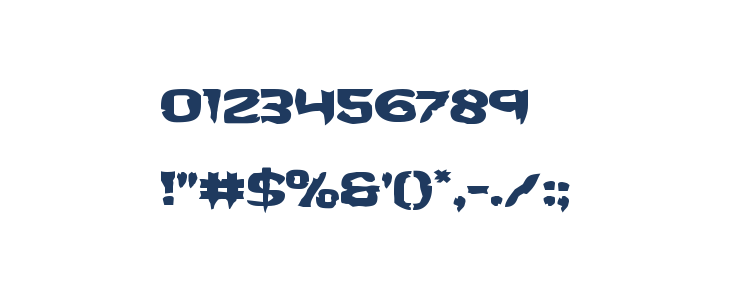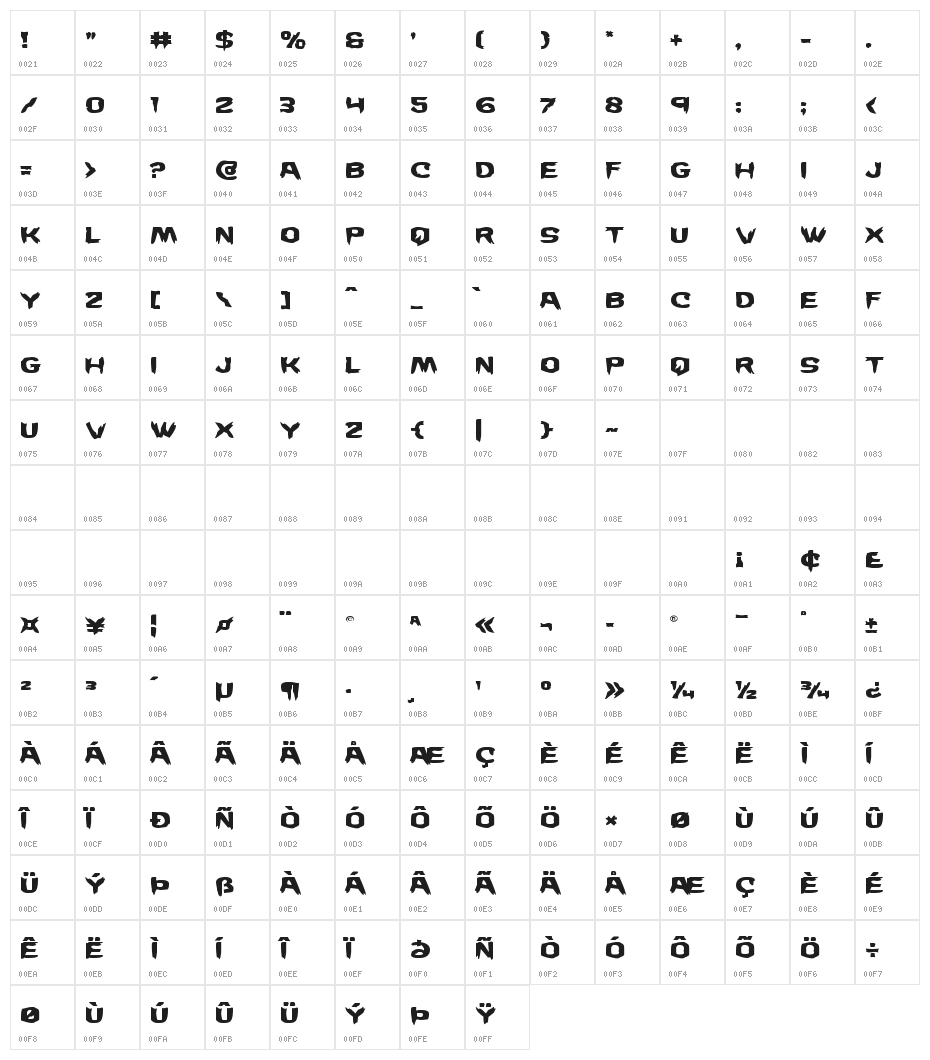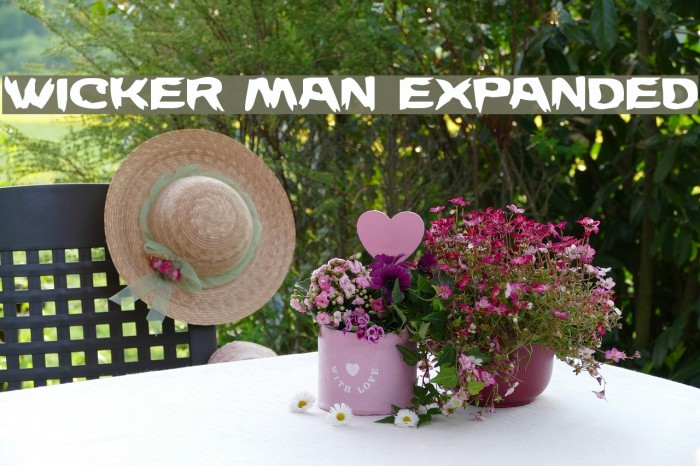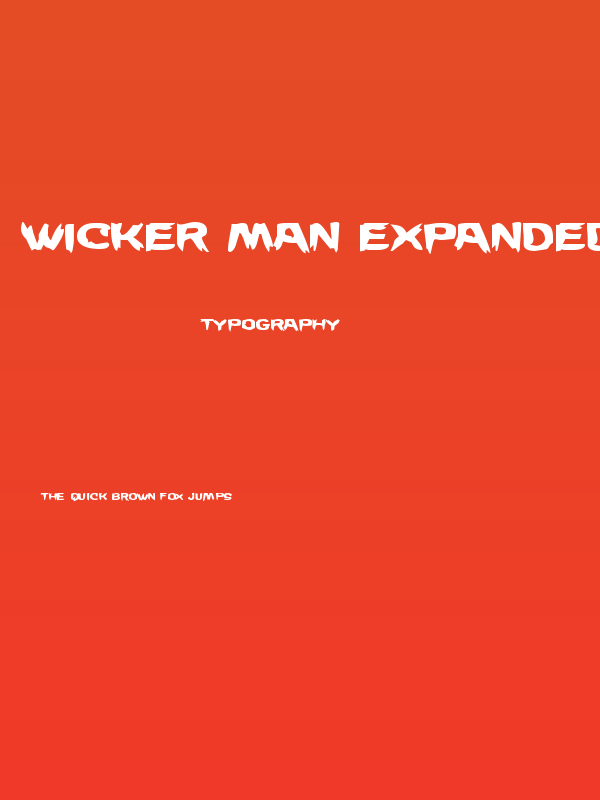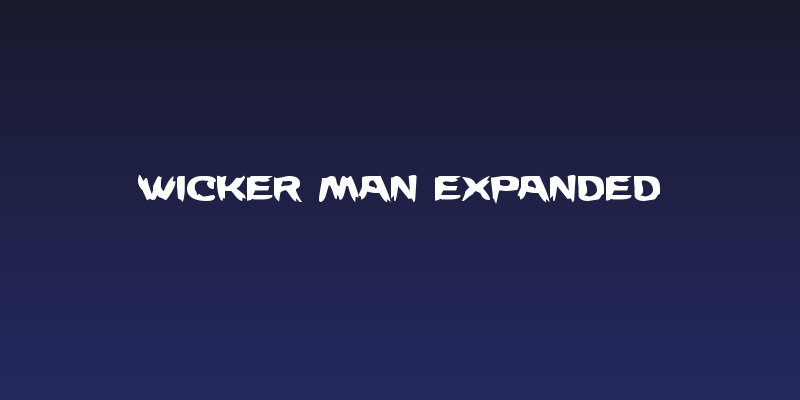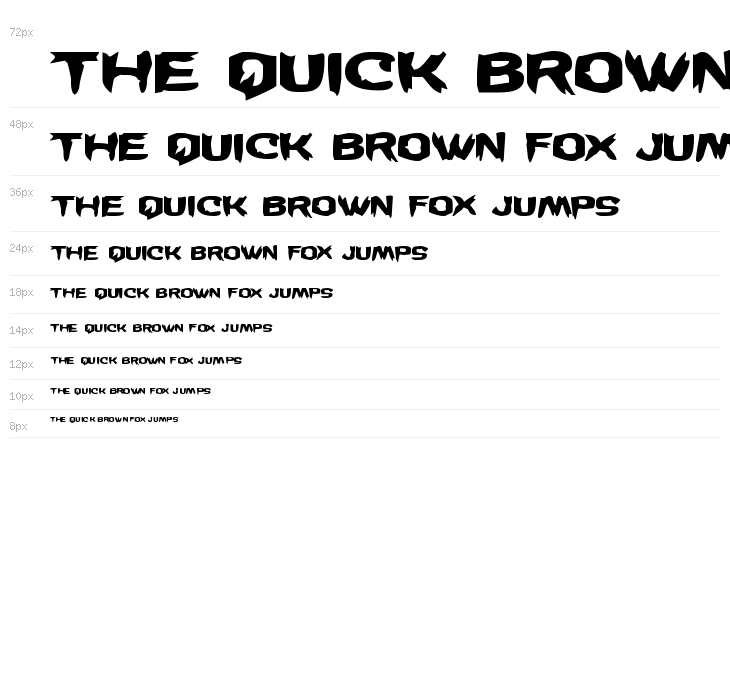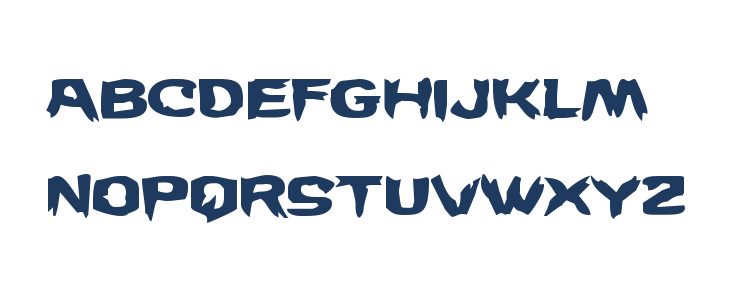
Wicker Man Expanded Font
✎ Thick
WICKER-MAN-EXPANDED 大写
WICKER-MAN-EXPANDED 小写
WICKER-MAN-EXPANDED 其它煤焦
| 名称 | Wicker Man Expanded |
| 重量 | Expanded |
| 分类 | Thick |
| 宽度 | Expanded |
| 推荐项目 | Ideal for horror-themed posters, album covers, video game titles, or any project needing a dramatic and intense aesthetic. |